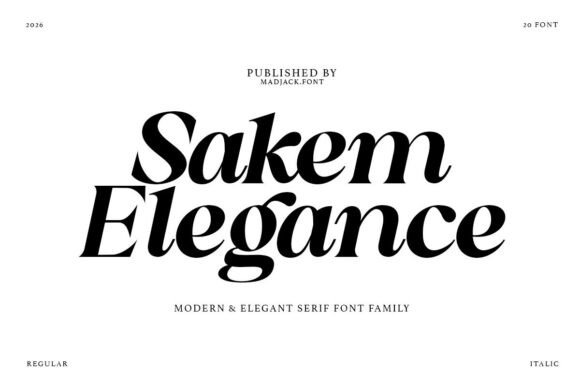
Sakem Elegance
Sakem Eleganceのような高品質の素材をお探しの場合、このプレミアムパッケージはクリエイティブなプロジェクトに素晴らしい選択です。
POD(オンデマンド印刷)製品、結婚式の招待状、またはソーシャルメディアのグラフィックを作成している場合でも、Sakem Eleganceは理想的です。